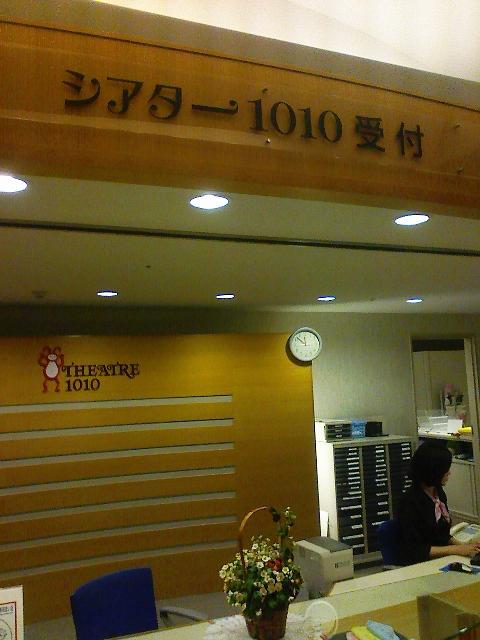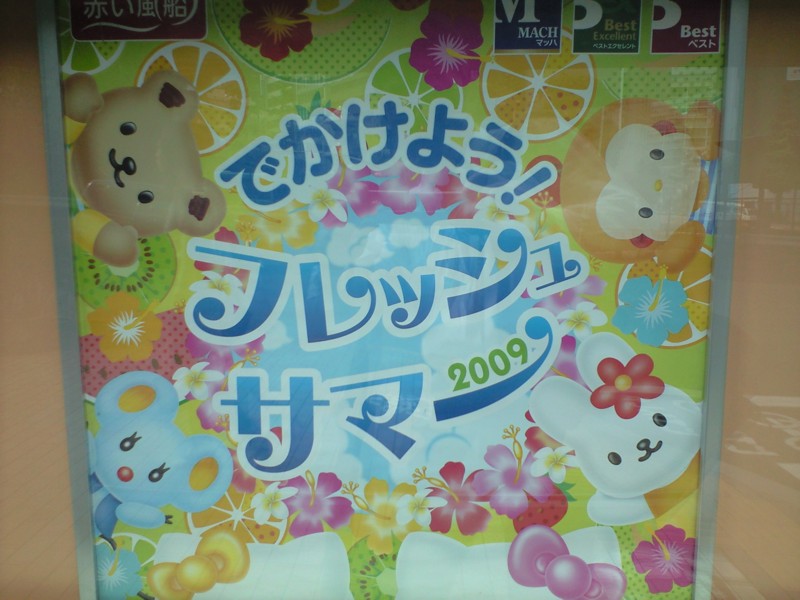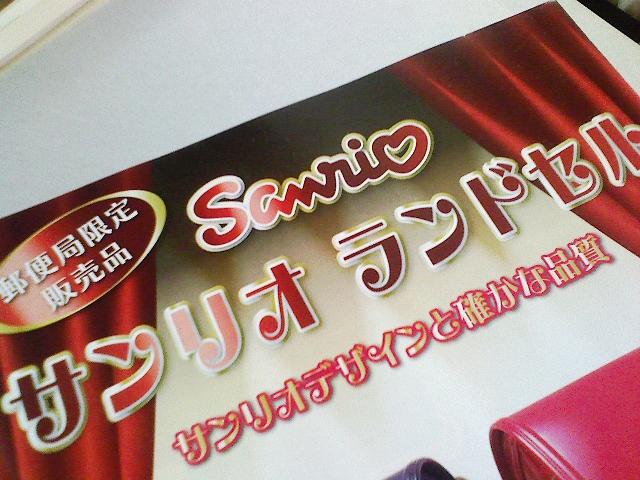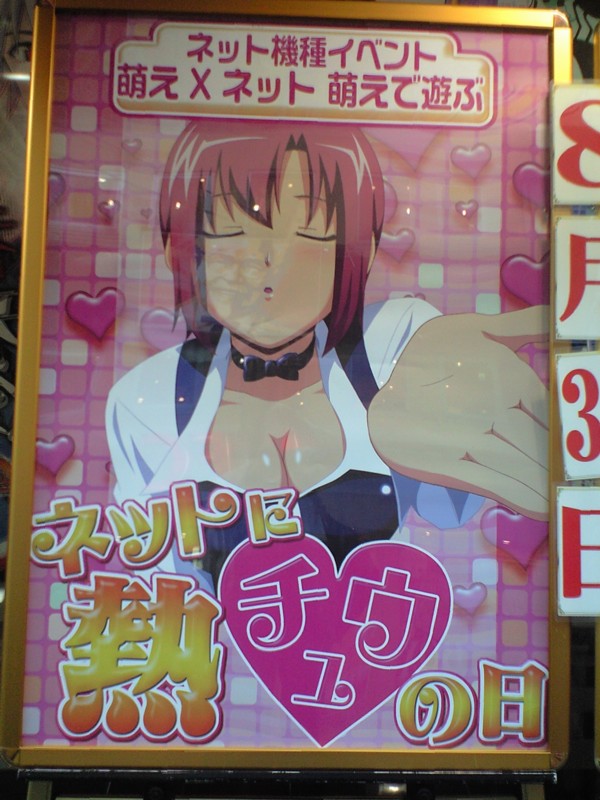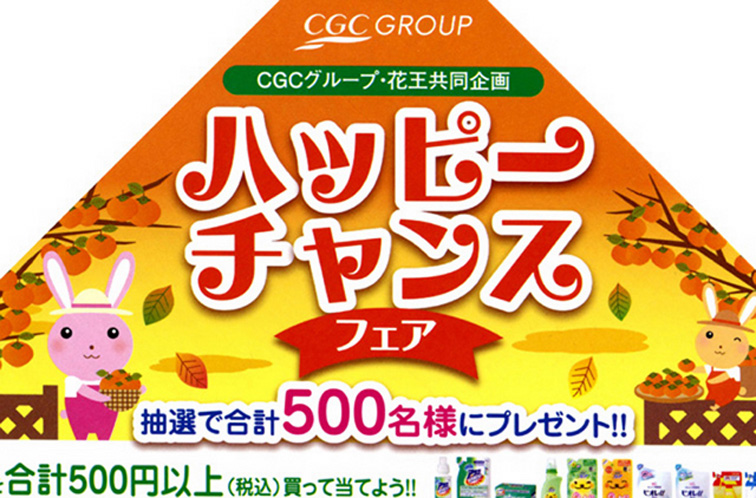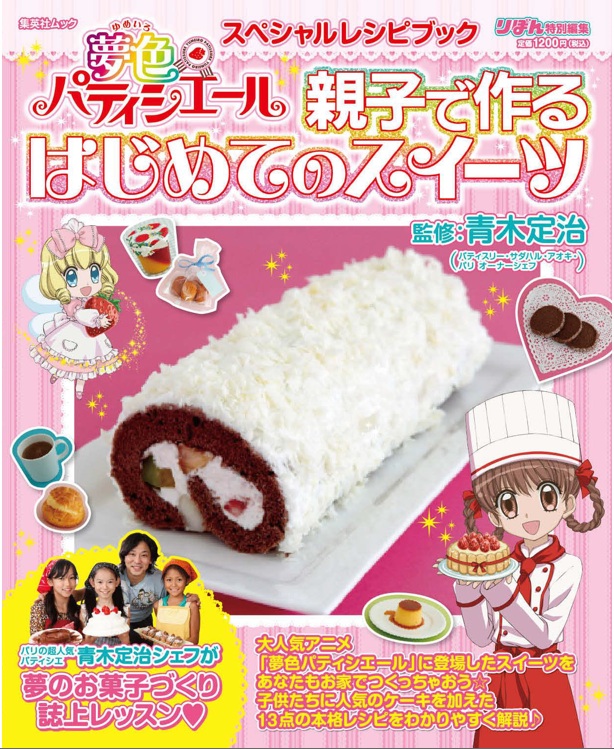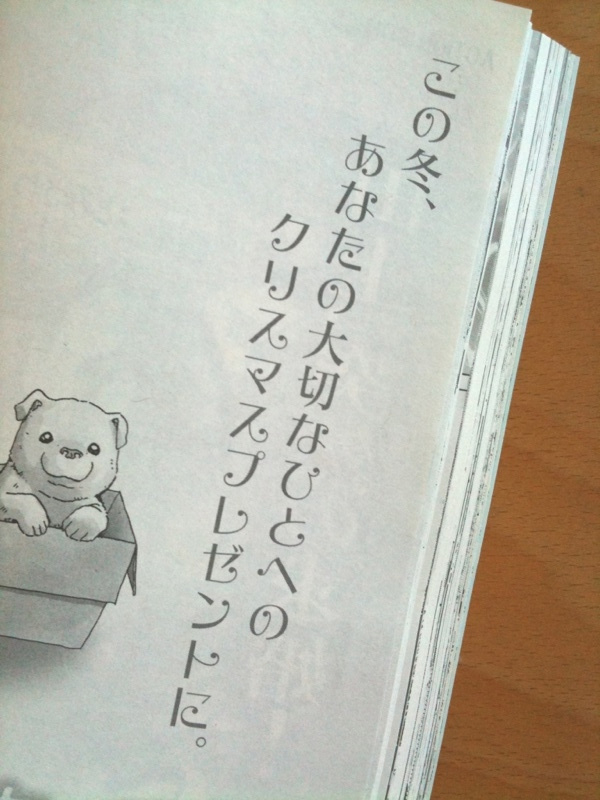
『TCG情報局』というカードゲームの番組にて  坂井和奏  2012年9月13日(木) 23:07
本日(2012年9月13日)東京MX、BS11で放送された『TCG情報局』という番組で「えれがんと」書体を見つけました。
女性声優(大久保瑠美という名前)の人が「津田ちゃん(津田美波、声優、女性)の愛があれば何もいりません」というやや危険な香りのする(世間ではこの現象を称して百合というらしい)テロップに「えれがんと」書体が使用され、なかなかいやらしい雰囲気を醸し出してました。
このテロップを見ていて気づいたのですが「ば」の字はエレメントがカールしてませんね。
なお、この女性声優さんは『ゆるゆり』という絶賛放送中の大人気アニメに出ているようです。
「エレメントがカールしていない文字」は、他にもありますので、探してみてくださいね。
洋菓子店のPOP  さとうゆたか  2012年9月4日(火) 16:06
濁音・半濁音がオリジナルのデザインではない。
無料お試しの清音フォント(笑)かな?
アニメ『TARI TARI』  坂井和奏  2012年8月28日(火) 1:15
絶賛放送中のアニメ『TARI TARI』のテロップ
普段、私が見ることがない番組なので、貴重な情報です。
酒の肴  さとうゆたか  2012年5月30日(水) 16:28
駅の売店で見つけて思わず買ってしまいました…。
チラシ広告  さとうゆたか  2012年4月29日(日) 15:13
旅行勧誘のチラシだったかな。
えれがんと書体の丸い部分が、さくらんぼの絵になっています。
アイドルグループ名  さとうゆたか  2012年4月8日(日) 9:19
人気急激上昇中!
トモとスザンヌ  さとうゆたか  2012年2月7日(火) 16:44
庄司智春(品川庄司)とスザンヌによるユニット名。
『スマイルプリキュア!』公式サイトにて  takumi  2011年12月5日(月) 15:40  HP
来年の春から放送予定の、『スマイルプリキュア!』というアニメの公式サイトで使われていました。
漢字部分は普通の明朝体ではなく、D社のR書体っぽいです。
面白い組み合わせだと思ったのですが、仮名との大きさや太さなどのバランスがちょっとどうかな〜…と抵抗を感じました。
確かに、カタカナが随分と小さく感じますね!
写真スタジオの店頭ポスター  さとうゆたか  2011年11月28日(月) 16:51
南千住を散歩中に見かけた。
記事タイトル  さとうゆたか  2011年11月17日(木) 17:04
芸能雑誌の相談コーナー。